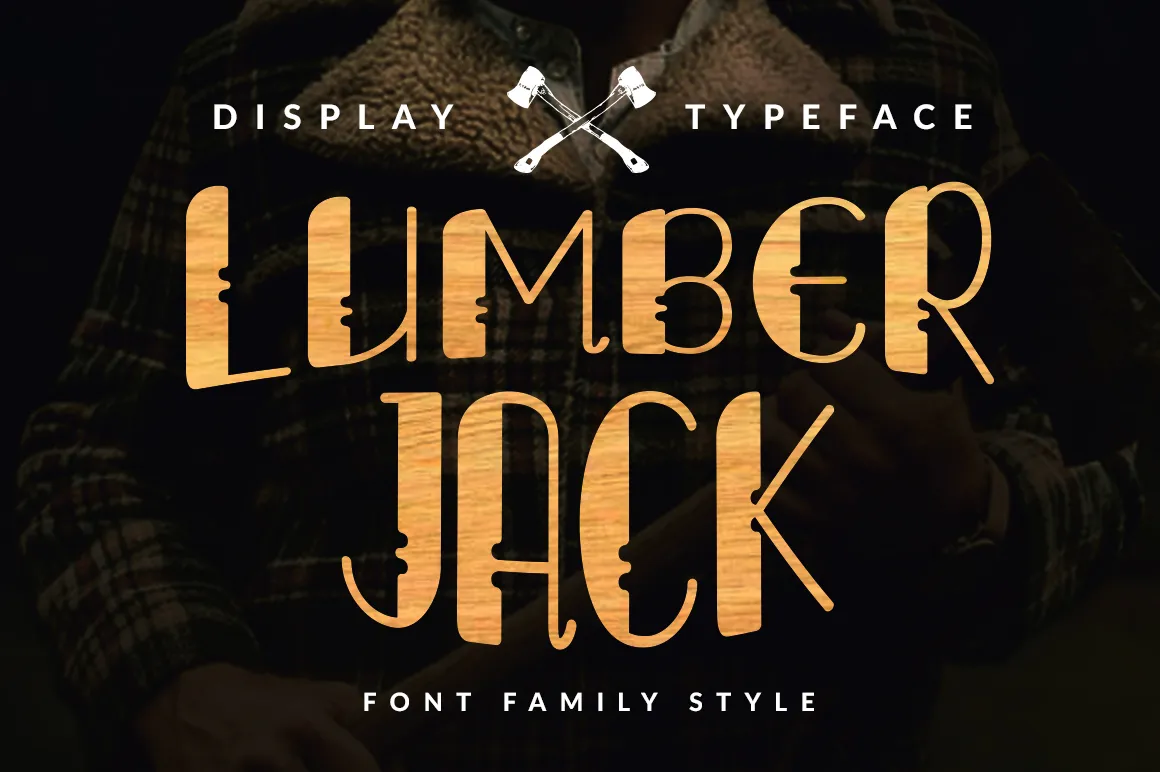
A Lumberjack Family Font é uma fonte display de Hamilton com um charme único e elegante que promete deixar sua próxima criação design mais marcante ainda. Esta fonte multifuncional pode ser usada em diversos ambientes, desde camisetas e cartões de visita até revistas e envelopes para festas. Seu design irradia confiabilidade e originalidade, o que a torna perfeita para os mais variados projetos gráficos. A Lumberjack Family Font é um conjunto robusto que inclui símbolos, pontuação e números, além de oferecer suporte a múltiplas línguas. Ela encaixa-se perfeitamente em diversos formatos – desde cartazes e logotipos até material para casamentos e cartões de agradecimento, demonstrando sua versatilidade e qualidade. Quer dar um toque único aos seus projetos? Experimente a Lumberjack Family Font. Isso pode ser o diferencial que você precisa para destacar seu design entre os demais.